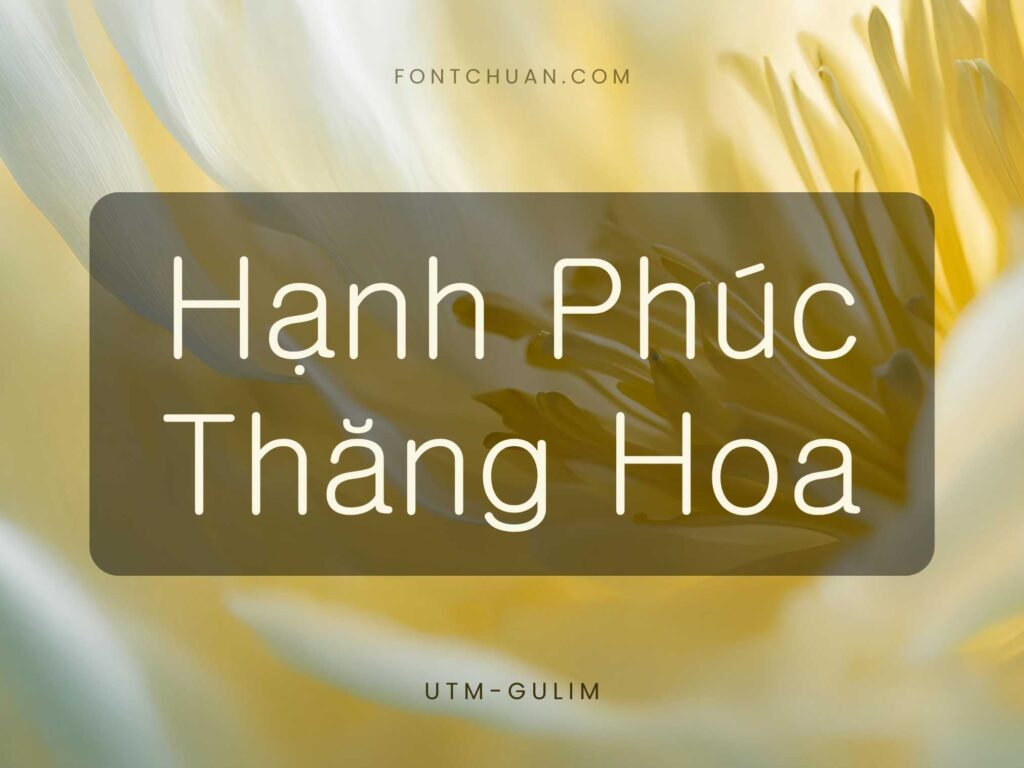
Font UTM Gulim Việt Hóa
UTM Gulim là một font chữ sans-serif đơn giản và dễ đọc, thường được sử dụng trong các thiết kế yêu cầu tính rõ ràng và chuyên nghiệp. Font này có nguồn gốc từ font Gulim, phổ biến trong hệ điều hành Windows và được ứng dụng rộng rãi trong nhiều lĩnh vực thiết kế. Font đã được Việt hóa bởi Thiên Minh, hỗ trợ đầy đủ tiếng Việt cùng hơn 200 ngôn ngữ khác, giúp mở rộng khả năng sử dụng. Thành viên của Font Chuẩn đã sưu tầm và giới thiệu font này nhằm đáp ứng nhu cầu bạn đọc, cung cấp nguồn tham khảo chất lượng và ứng dụng thực tế vào các dự án thiết kế. Ngoài ra, UTM Gulim cũng có thể kết hợp với Font Monospace trong các dự án kỹ thuật số hoặc lập trình, nhờ sự tương đồng về khả năng hiển thị rõ ràng và tối ưu cho văn bản dài.
Về đặc điểm thiết kế, UTM Gulim có các nét chữ gọn gàng, độ dày đồng đều và không có chân, mang lại cảm giác hiện đại và dễ tiếp cận. Font này phù hợp với nhiều ứng dụng, từ văn bản hiển thị trên màn hình đến thiết kế đồ họa, trình bày tài liệu và bảng hiệu. Các ngành nghề như công nghệ, giáo dục, quảng cáo và thiết kế thương hiệu có thể tận dụng font này để tạo nên sự chuyên nghiệp và dễ đọc trong các sản phẩm thiết kế của mình